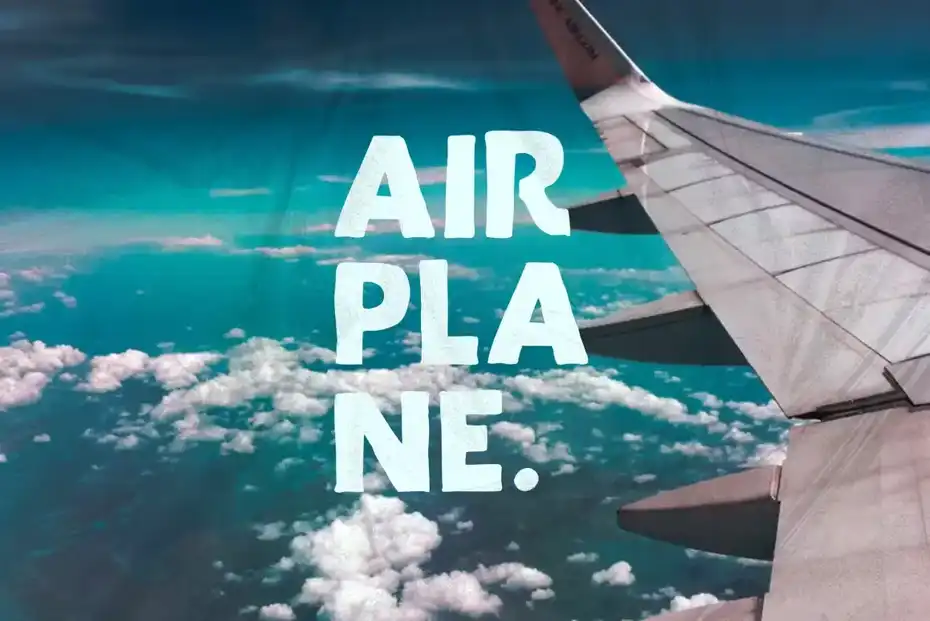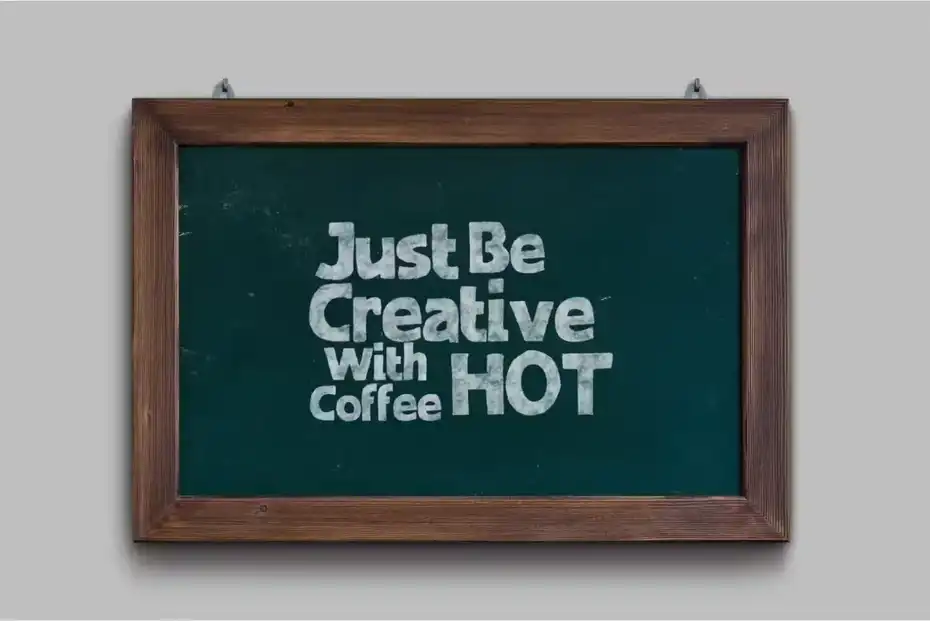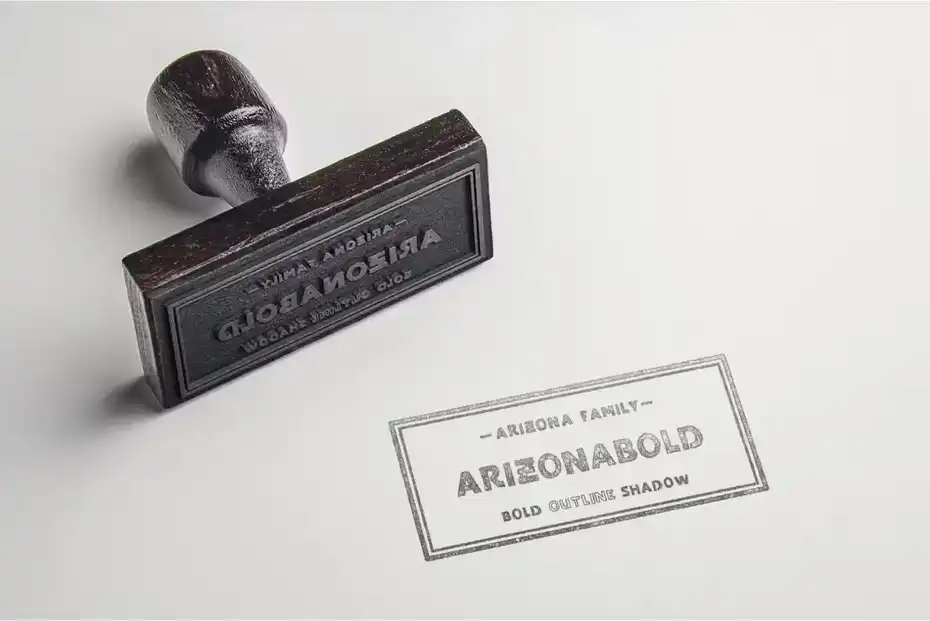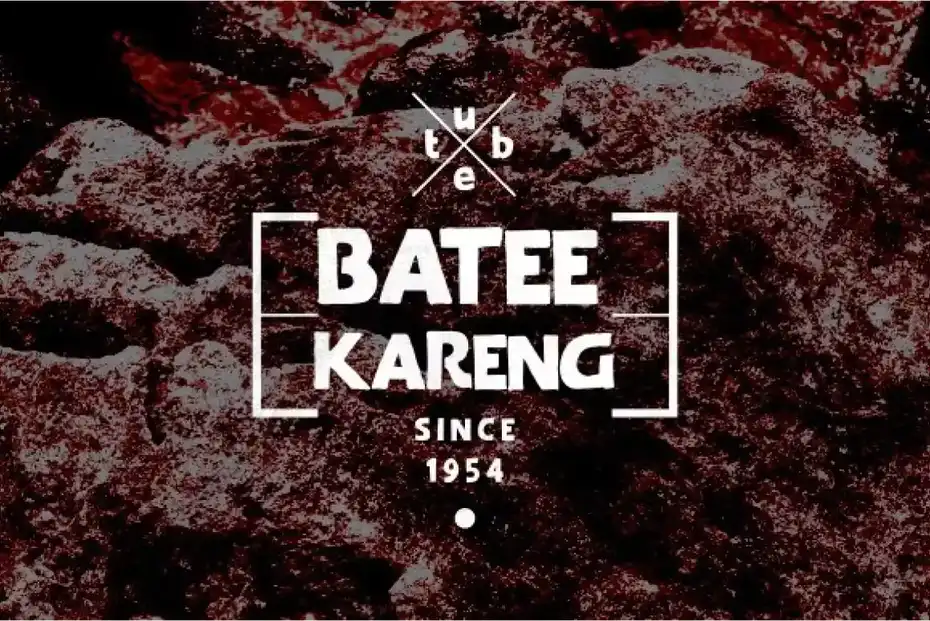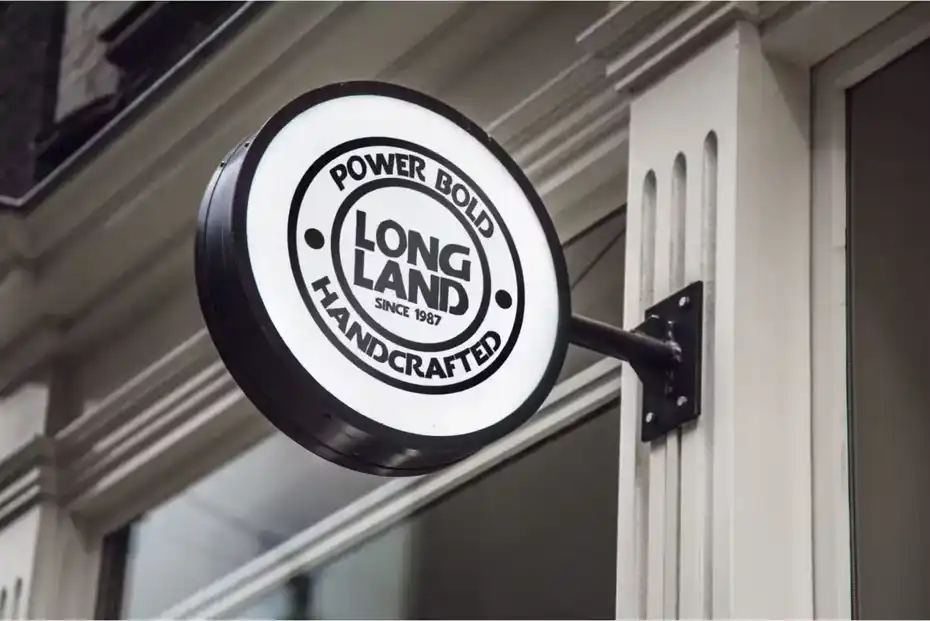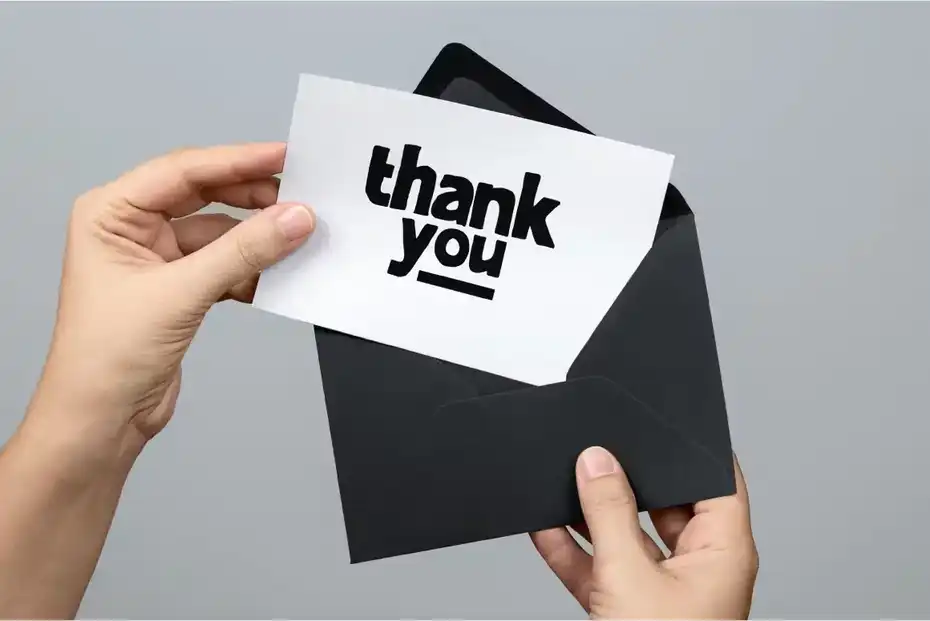
دانلود فونت انگلیسی مدرن Arizona Family Font
فونت انگلیسی مدرن Arizona Family Font : این مجموعه شامل یک فونت انگلیسی مدرن است که برای لوگو، برندینگ، کارت دعوت عروسی، سربرگ، برچسب، روزنامه، پوستر، تیشرت و غیره مناسب میباشد.